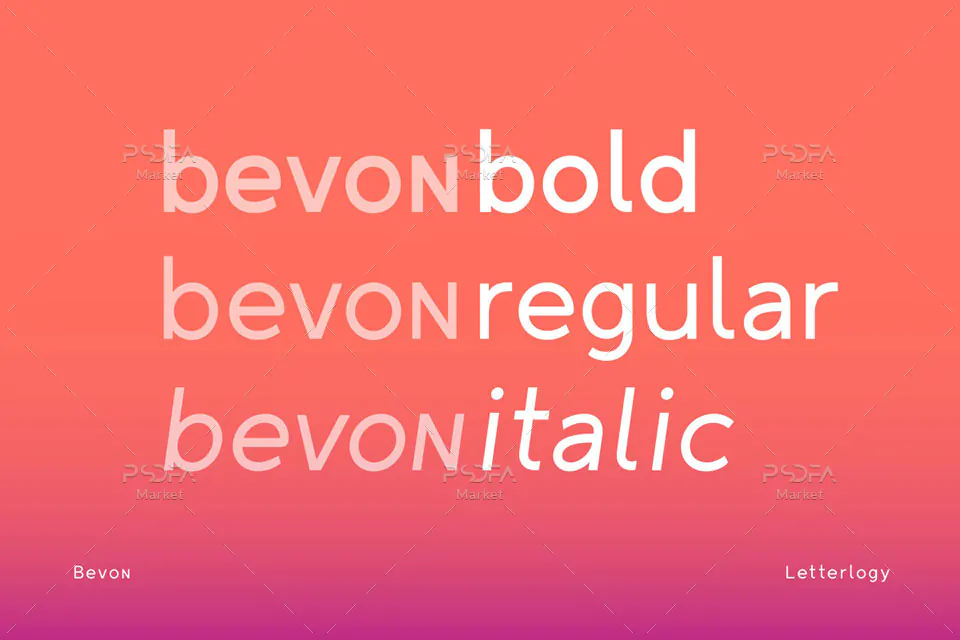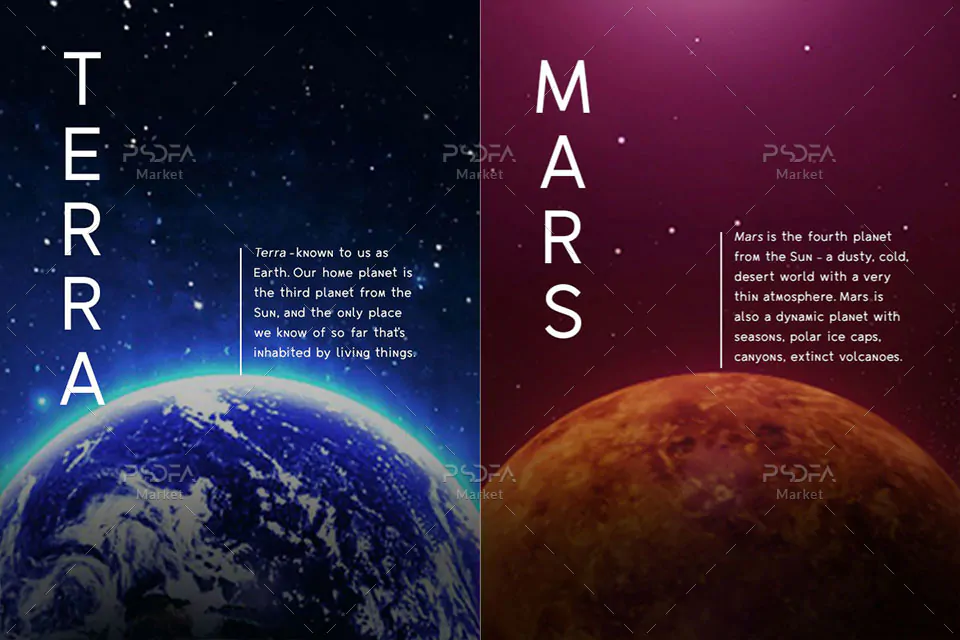
فونت سنس سریف انگلیسی Bevon
فونت سنس سریف انگلیسی Bevon یک قلم زیبای انگلیسی است که با سه وزن مختلف طراحی شده است که میتوانید از آن در تایپ متون استفاده کنید. این فونت زیبا در قالب فایلهای OTF, TTF در فایل محصول قرار دارد که با نصب یکی از این 2 فرمت در پوشه فونتهای سیستم میتوانید از این فونت انگلیسی در تمام نرم افزارهای گرافیکی و تایپ متون همچون فتوشاپ، افتر افکت، پریمیر، ورد، پاورپوینت و … استفاده کنید.
فونت Bevon در سه وزن معمولی (Regular)، ضخیم (Bold) و مورب (Italic) طراحی شده است که مناسب جهت استفاده در تایپ متون، تیتر و عناوین طرحهای گرافیکی مختلف همچون بروشور، تراکت، پوستر، کارت ویزیت، نامههای اداری و … کاربرد دارد.